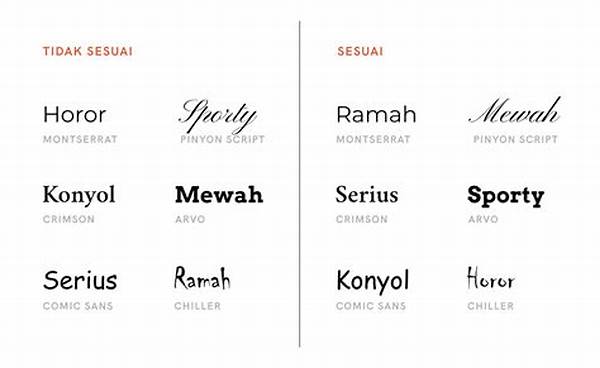
Pernahkah Anda merasa bahwa huruf yang dipilih untuk sebuah logo atau kampanye iklan dapat memengaruhi bagaimana Anda memandang suatu merek? Yup, ternyata font yang dipilih bisa berbicara banyak tentang identitas sebuah brand. Memilih font bukan hanya soal estetika, tetapi juga soal bagaimana pesan yang ingin disampaikan diterima dengan baik oleh audiens. Mari kita lihat lebih dalam tentang pemilihan font untuk branding ini!
Mengapa Pemilihan Font untuk Branding Itu Penting?
Pertama-tama, kita perlu menyadari betapa kuatnya dampak dari pemilihan font untuk branding sebuah bisnis. Font yang tepat dapat mengomunikasikan nilai-nilai inti dari merek Anda, menarik perhatian, dan membuat pesan Anda lebih mudah diingat. Coba bayangkan, sebuah perusahaan teknologi memilih font bergaya kuno? Tentu pesan yang diterima audiens bisa berbeda dari yang diharapkan.
Memilih font bisa menjadi langkah awal untuk membangun persepsi yang kuat tentang merek Anda. Misalnya, font serif mungkin memberikan kesan tradisional dan terpercaya, sementara font sans-serif menawarkan kesan modern dan sederhana. Setiap jenis font memiliki karakteristik unik yang dapat mempengaruhi bagaimana audiens merespon merek Anda.
Lebih jauh lagi, pemilihan font untuk branding juga berpengaruh pada konsistensi visual merek Anda. Konsistensi ini penting untuk membangun kepercayaan dan pengakuan dari audiens. Jadi, ketika berbicara tentang branding, jangan hanya fokus pada logo atau warna, tetapi juga pada font yang digunakan. Pastikan Anda memilih font yang benar-benar mewakili identitas merek Anda.
Tips Memilih Font yang Pas untuk Branding
1. Pahami Identitas Merek
Ketahui siapa Anda dan apa yang ingin Anda sampaikan sebelum memilih font. Pemilihan font untuk branding harus bisa mencerminkan karakter dan nilai merek Anda.
2. Perhatikan Keterbacaan
Terlihat keren tapi sulit dibaca? Hindari font yang membuat audiens harus berusaha keras untuk memahaminya. Pilih yang mudah dibaca agar pesan tersampaikan dengan baik.
3. Sesuaikan dengan Audiens
Font yang dipilih harus cocok dengan target audiens. Mungkin font quirky cocok untuk anak muda, tapi tidak untuk perusahaan keuangan.
4. Konsistensi adalah Kunci
Pastikan font yang dipilih digunakan secara konsisten di seluruh materi pemasaran Anda. Konsistensi akan memperkuat identitas merek.
5. Eksperimen dengan Variasi
Jangan takut untuk mencoba kombinasi font, tapi pastikan tetap harmonis. Variasi yang tepat dapat menambah daya tarik visual.
Mitos dan Fakta Tentang Pemilihan Font untuk Branding
Banyak orang beranggapan bahwa semua font sama saja asal terlihat menarik. Namun, dalam pemilihan font untuk branding, itu jelas bukan sekadar memilih yang terlihat bagus. Font harus mencerminkan kepribadian merek dan sesuai dengan audiens yang ditargetkan.
Ada juga mitos bahwa font yang sederhana selalu lebih baik. Walau kesederhanaan sering menjadi pilihan aman, namun terkadang font dengan sedikit karakter bisa memberikan keunikan tersendiri. Yang penting adalah kesesuaian dengan identitas merek. Fakta lainnya, ketika sebuah font digunakan secara konsisten, itu dapat membantu meningkatkan pengenalan merek di mata audiens.
Kesalahan yang Sering Terjadi dalam Pemilihan Font untuk Branding
Meski terdengar sepele, pemilihan font acap kali membuat beberapa merek melakukan kesalahan. Pertama, memilih font hanya berdasarkan tren. Meskipun mengikuti tren itu menarik, namun tren bisa berubah-ubah. Lebih baik pilih font berdasarkan karakter merek.
Kesalahan lain adalah mengabaikan keterbacaan. Terlalu berfokus pada estetika bisa membuat Anda lupa pada fungsi utama tulisan, yaitu dibaca. Ada juga yang terlalu banyak menggunakan variasi font dalam satu produk, yang mengakibatkan kebingungan bagi audiens. Pemilihan font untuk branding sebaiknya tetap simpel namun bermakna.
How to Master the Art of Choosing Fonts for Branding
Mastering pemilihan font untuk branding memang tidak mudah, perlu latihan dan pemahaman yang mendalam. Sebelum melangkah, cobalah untuk melakukan riset kecil-kecilan tentang kompetitor. Amati font yang mereka pilih dan bagaimana efeknya.
Kemudian, uji coba font pada beberapa platform sebelum memutuskan untuk menggunakannya secara permanen. Ini dapat memberikan gambaran bagaimana font tersebut bekerja dalam berbagai media. Jangan lupa untuk meminta feedback dari orang lain, karena pandangan dari sudut yang berbeda penting untuk mendapatkan hasil terbaik.
Strategi Mengembangkan Branding Melalui Pemilihan Font
Seringkali, keberhasilan dalam branding ditentukan oleh strategi yang matang, termasuk dalam pemilihan font. Pertama-tama, pastikan untuk melakukan eksplorasi visual secara menyeluruh. Jangan terburu-buru dalam menentukan pilihan karena pemilihan font yang tepat bisa menjadi investasi jangka panjang untuk merek Anda.
Pemilihan font untuk branding juga bisa mendukung story-telling dari produk atau layanan yang ditawarkan. Jadi, pilihlah font yang bisa ikut ‘berbicara’ tentang cerita tersebut. Contohnya, jika produk Anda bersifat ramah lingkungan, font yang organik dan natural bisa jadi pilihan. Integrasikan pilihan font ini dengan elemen branding lainnya untuk hasil maksimal.
Namun, perlu diingat, font hanyalah salah satu elemen dalam branding. Harmoni, konsistensi, dan kesesuaian adalah prinsip-prinsip yang harus dipegang teguh. Pemilihan font yang tepat dapat menjadi batu loncatan menuju brand yang kuat dan dikenal luas. Selalu lakukan evaluasi secara berkala dan jangan ragu untuk melakukan perubahan jika diperlukan, demi kebaikan dan keberlanjutan brand Anda.